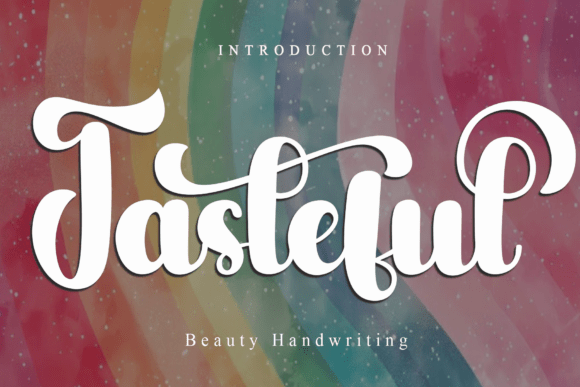
Tasteful
Review Completo da Fonte “Tasteful”: Elegância Hand‑written para Seus Projetos
Se você busca uma tipografia que una sofisticação e contemporaneidade, a Tasteful é a escolha ideal. Inspirada na caligrafia clássica atemporal, essa fonte manuscrita traz um visual estilizado que eleva qualquer peça criativa, seja branding, convites ou design editorial.
Por que a Tasteful se destaca?
- Design equilibrado: traços finos e variações de peso que garantem legibilidade sem perder o charme artesanal.
- Atmosfera contemporânea: combina a tradição da caligrafia clássica com um toque moderno, perfeito para projetos atuais.
- Versatilidade: funciona bem em títulos, subtítulos, logotipos e até em textos curtos, adaptando‑se a diferentes estilos visuais.
- Qualidade impecável: cada caractere foi cuidadosamente desenhado, evitando imperfeições comuns em fontes manuscritas genéricas.
Aplicações Ideais da Tasteful
- Invitações de casamento e eventos especiais;
- Identidade visual de marcas premium;
- Capas de livros e revistas de lifestyle;
- Postagens de mídia social que precisam de um toque artesanal;
- Materiais de marketing impressos, como flyers e brochuras.
Prós e Contras
- Pró: Elegância natural que destaca seu conteúdo.
- Pró: Excelente legibilidade mesmo em tamanhos pequenos.
- Pró: Conjunto completo de caracteres latinos, incluindo acentos.
- Contra: Por ser muito estilosa, pode não ser adequada para textos longos.
A fonte Tasteful entrega exatamente o que promete: um visual manuscrito sofisticado, equilibrado e pronto para transformar seus projetos em obras‑de‑arte. Se a sua marca busca transmitir refinamento e originalidade, invista nesta tipografia e sinta a diferença nas suas criações.